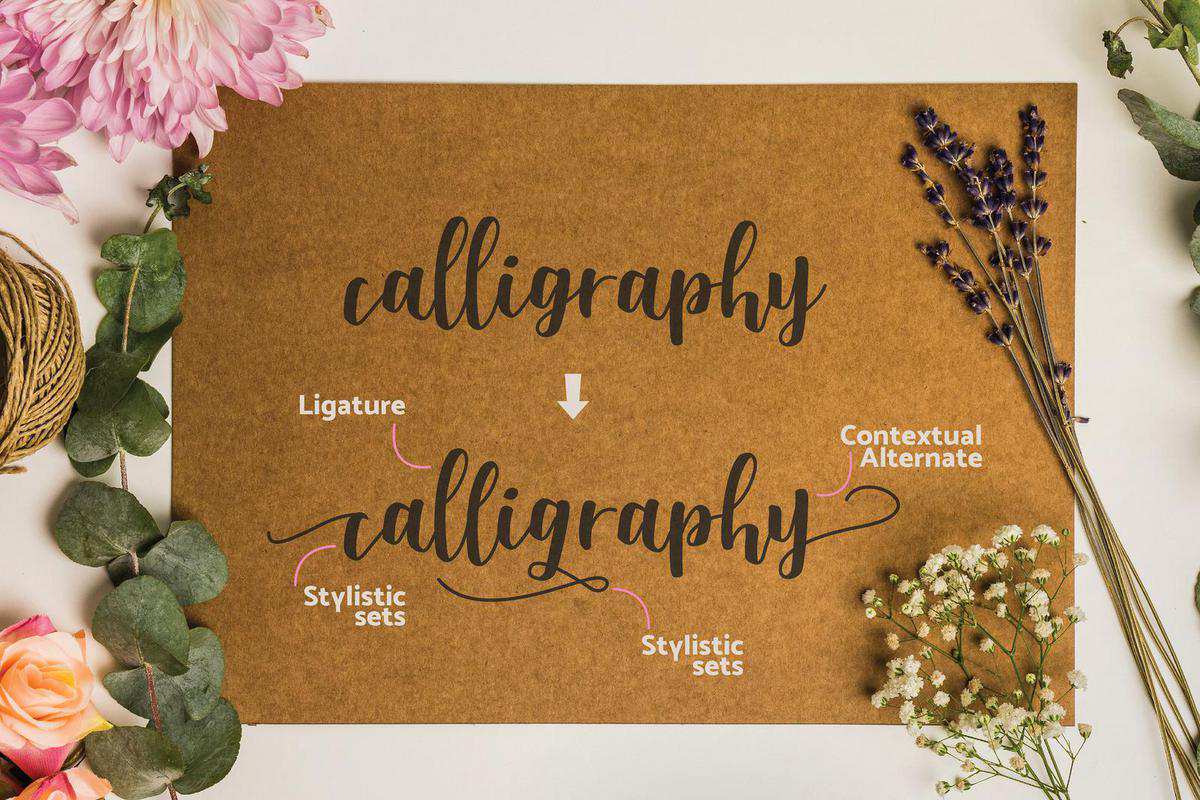
ShellaFontTrio.A和Brushed,有趣,温暖,舒适的字体组合,具有3种不同的风格。ShellaFontTrio与ShellaSensor Shellaro相结合,使每一个词都具有独特性。适用于任何设计需求,现代活力设计,品牌,文具设计,博客设计,现代垂直设计,邀请,艺术报价,家居装饰,书籍/封面,邀请,特色,生日,定制马克杯、枕头、t恤、任何刷字需求和更多。ShellaFontTrio.A和刷字、有趣、温暖、舒适的三种不同风格的组合。Shellacanf与Hellas或Shellararough Font相结合,以保持每个词的独特性。适用于任何设计需求、现代活力设计、品牌、文具设计、博客设计、现代垂直设计、邀请、艺术报价,家居装潢、书籍/封面、邀请、特价品、生日、定制马克杯、枕头、t恤、任何毛笔书写需求等。